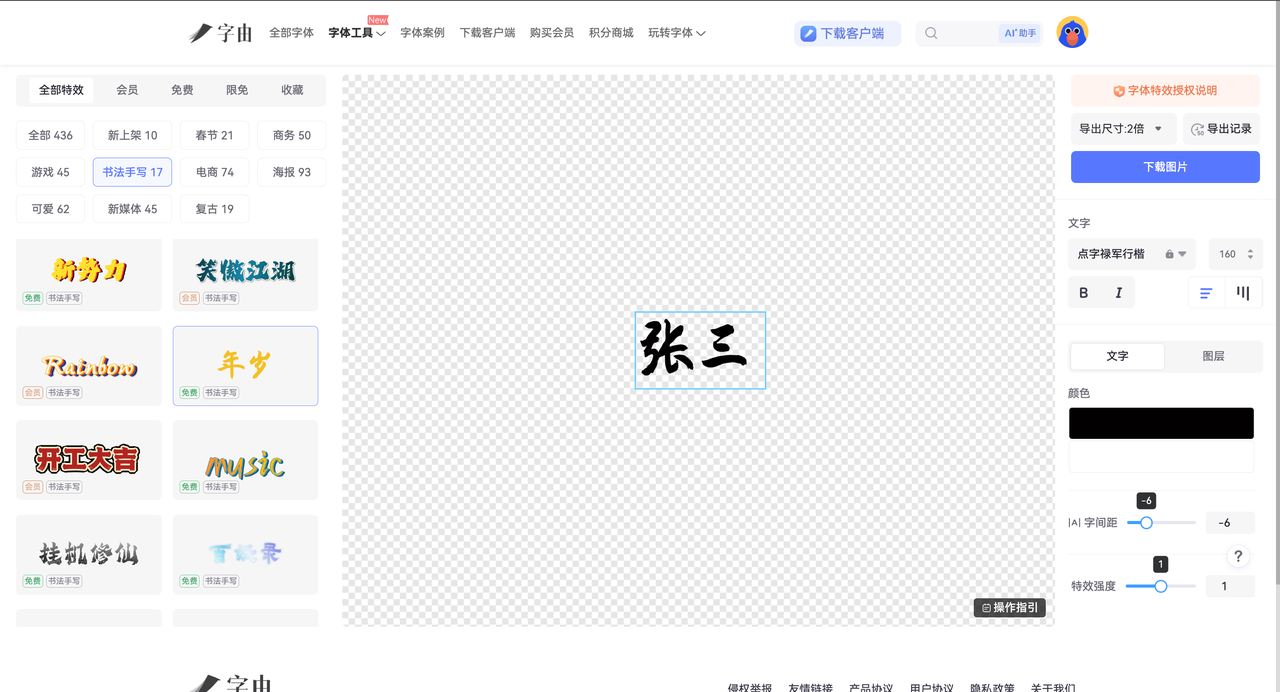
在线制作电子签名完整指南,3分钟搞定手写签名
说实话,很多人搜在线制作电子签名,表面上是在找一个能写字、能下载 PNG 的小工具,真到了要用的时候,问题就变了:签名图发虚怎么办?放进 PDF 里怎么总有白底?客户要的是“图片签名”,还是“可追踪的电子签约”?有时候你可能需要签一个合作协议,用了一个很常见的免费在线签名生成器。生成出来的签名很整齐,但也很假——电子签名不仅是一个功能,更是一个“身份表达”。如果太工整,它不像手写;如果太潦草,它又不专业。所以这篇文章,我不打算只教你怎么做,而是告诉你:如何做一个既真实、又好看的电子签名。
1、在线制作电子签名工具到底该怎么选?
如果你的目标只是做一个透明底签名图,用在 Word、PDF、WPS、表单或者邮件里,那你要优先看 4 件事。
- 第一,能不能手写签名生成,因为打字签名通常更像“姓名样式”,不够自然。
- 第二,能不能导出透明底 PNG,这决定了你把它放进深色背景或扫描件时会不会露白边。
- 第三,操作是不是够快,最好 1 分钟内完成。
- 第四,文档里有没有额外的编辑能力,比如日期、文本、复选框。
2、在线制作电子签名其实有两种完全不同的方法
在讲工具之前,我先帮你把逻辑理清楚。现在主流的在线制作电子签名的方法,其实分两类:
- 第一种,是“直接生成型”。也就是输入名字,然后系统帮你生成一个签名。
- 第二种,是“设计型”。通过字体、手写风格、特效去组合出一个更个性化的签名。
很多人默认用第一种,但我现在几乎只用第二种。原因很简单:
👉 第一种快,但容易“撞签名”
👉 第二种稍微多一步,但更像你本人
接下来我会重点讲第二种方法,也就是我现在长期在用的方式。
3、用字由制作电子签名(完整流程)
字由不是传统意义上的电子签名生成平台,但如果你的需求是“把在线制作电子签名这件事做得更好看、更专业、更适合设计落地”,它非常适合放在第一位。字由官网显示,平台提供 5000+ 精选字体、支持在 PS、AI、ID、XD、Figma、Sketch、CDR 等软件里一键应用字体,并提供 AI 识字、字体特效、个人云字库等功能;如果你做的是品牌签名封面、签名海报、邮件签名视觉图,字由能明显拉开质感。免费版就能用免费商用字体和基础 AI 识字。
我的体验感受是,很多人把在线制作电子签名当成“写个名字”就结束了,但落到设计稿里,签名周围的标题字、日期字、说明字一旦风格不搭,整张图就很廉价。字由解决的正是后半段:你把签名图做出来以后,旁边的姓名、职位、落款、封面标题,可以直接在设计软件里一键换字,省掉找字、装字、对授权的焦虑。
如果你希望你的签名:
- 更像手写签名
- 可以反复使用
那这个方法基本可以直接用。这一部分我会写得非常具体,你可以边看边操作。
Step 1:确定签名风格(很多人会跳过)
在开始之前,你先想一个问题:你的签名是偏正式,还是偏个性?比如:
- 合同签名 → 建议偏稳重
- 自媒体签名 → 可以更有设计感
这一步看起来简单,但会直接影响后面的效果。
Step 2:进入字由字体特效或AI字体页面
你可以选择两种方式:
(1)字体特效(适合快速生成)
(2)AI字体(适合做更个性化签名)
Step 3:输入你的名字
在输入框中输入你的名字,比如“张三”或英文名。这里有个小技巧,你可以尝试不同写法,比如:全名、名字缩写、中英文混合。我自己一般会生成 3-5 个版本,然后挑一个最顺眼的。
Step 4:选择手写风格字体
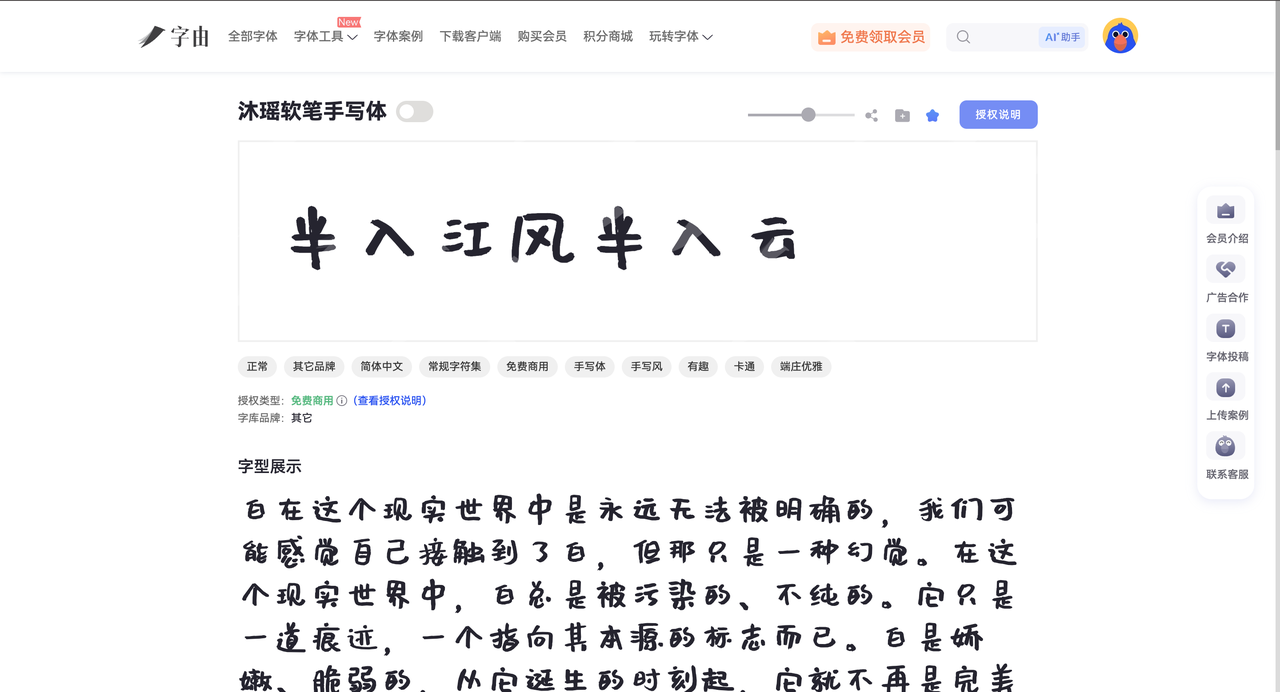
Step 5:调整细节
这是很多人忽略的一步,但其实最关键。你可以调整:
- 字距(稍微拉开一点更自然)
- 粗细(太粗会显得不真实)
- 颜色(建议深灰或黑色)
- 描边(尽量少用)
我自己的经验是:签名越简单,越真实
Step 6:导出签名
完成之后,你可以直接导出PNG图片。建议选择透明背景和高清分辨率。这样可以直接用于合同、Word、PDF等文件。
Step 7:应用到实际场景
如果你在PS、Word或者设计软件中使用,可以直接导入签名图片。如果你使用字由客户端,还可以实现字体一键应用,这一步会大幅提升效率。
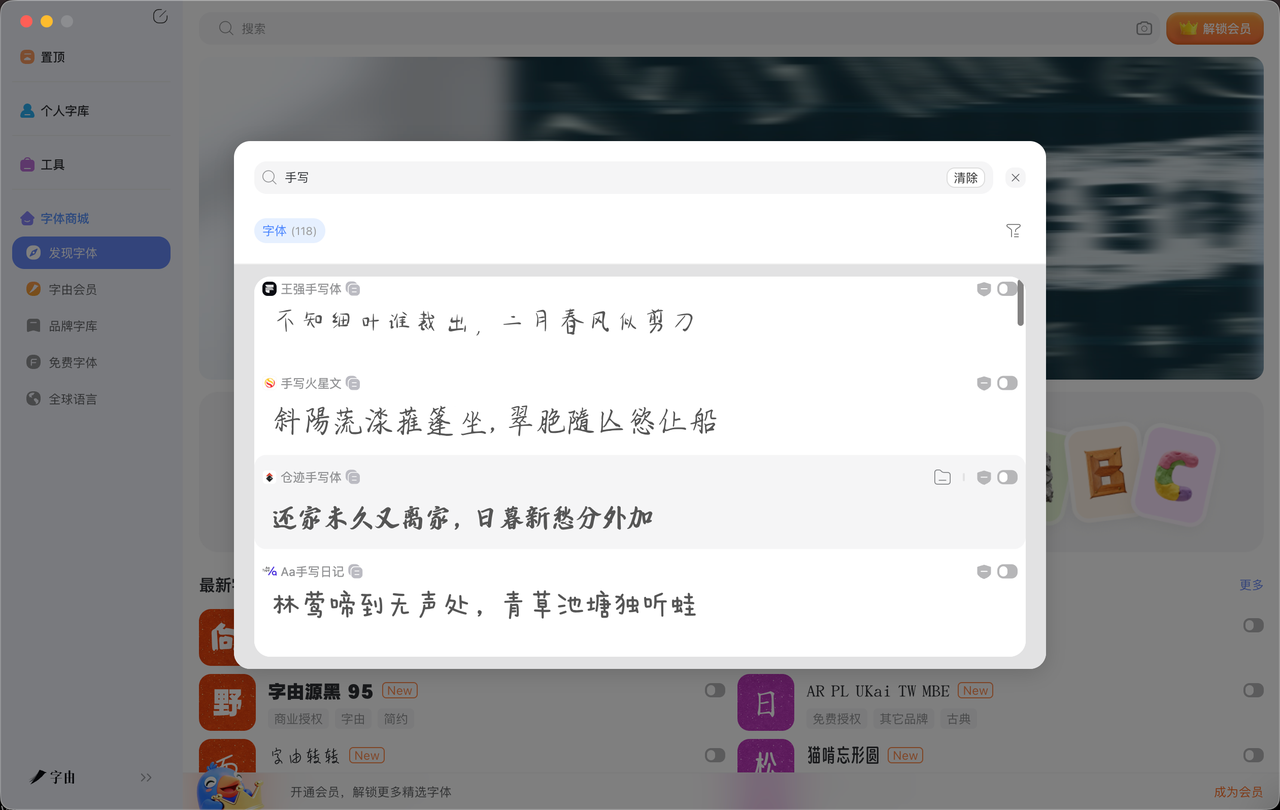
4、字由比普通免费在线签名生成器强在哪?
说几个真实差别。
- 第一,字体质量更高。很多免费在线签名生成器用的是通用字体,看起来很“模板化”。
- 第三,可以持续优化。你可以随时回来调整签名,而不是一次生成就结束。